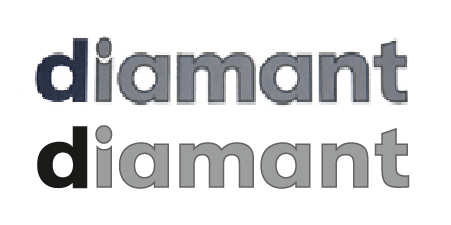
Dringend Schriftart gesucht!
kann mir jemand bei der Suche nach folgender Schriftart (Bild) helfen?
Es drängt sich mir der Eindruck auf dass da nicht nur eine Schriftart verwendet wurde (oder doch?) … und diese zudem vertikal gequetscht wurden. Das i ist wohl mundgebissen.
käme ganz gut hin, wenn du sie auf auf 75 % Höhe zusammenstauchst.
Ich glaube auch daß da mehrere Schriften verwendet wurden... nur welche?
Gibt es noch andere Möglichkeiten?
Wenn Du von der fetten Avant Garde ausgehst, die ja auf der Futura basiert, dann mal mit der Dampfwalze drüberfährst (die Schrift ist definitiv breitgeklopft, das siehst Du am Verhältnis der horizontalen / vertikalen Strichstärken) und das i hinbastelst, hast Du schon alles bis auf das t. Und das kann sonstwo hergeholt sein.
Es geht darum das Logo neu zu erstellen, sollte aber nach Möglichkeit dem Original sehr ähneln.
Das mit der Vorlage dürfte schwierig werden.
Das Logo wurde von irgendeinem Briefkopf gescannt
und mehr ist nicht aufzutreiben, leider, sonst wäre das
denke ich kein Problem. Kopfzerbrechen bereiten mir vor allem das
"gequetschte" d am Anfang.
das wäre also höchste zeit das gequetschte einfach wegzulassen, ich wette, dass es niemand merken wird und wenn dann kannst du es erklären, dass es bestimmt ein versehen war :roll:
Es gibt doch noch eine Lösung …
Ich hab das mal aus dieser ungequetscht nachgebastelt, nur das t wurde unten rechts etwas nachbearbeitet und beim d die Oberlänge verkürzt.